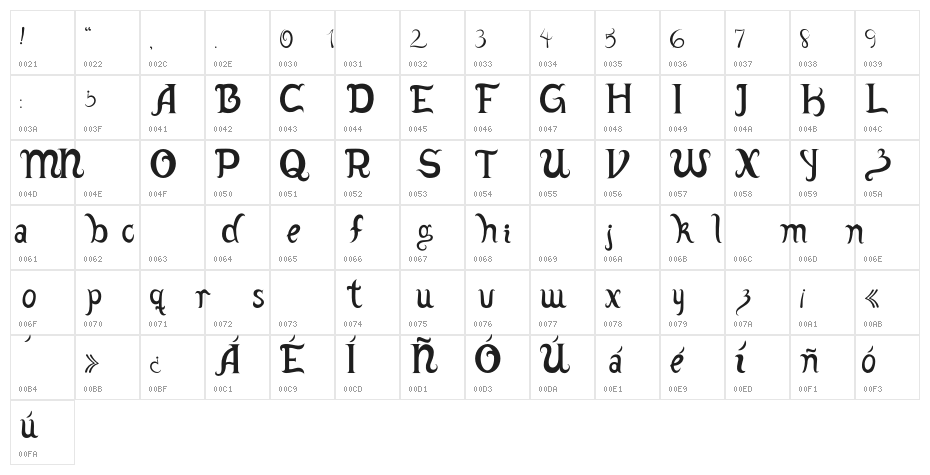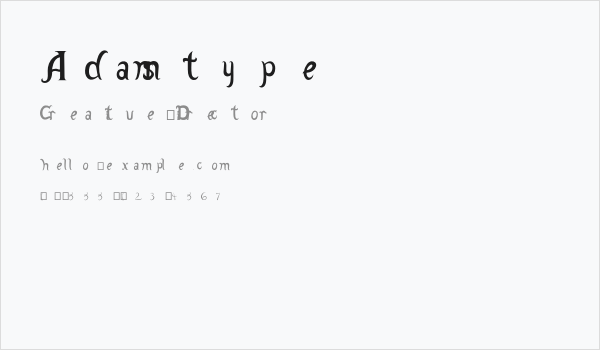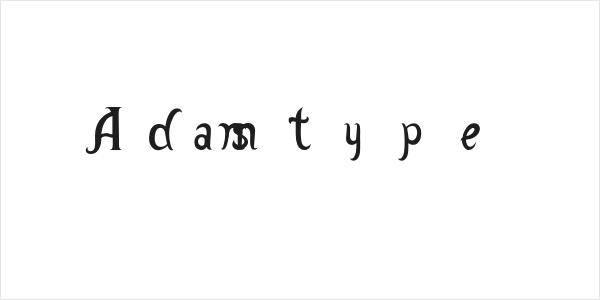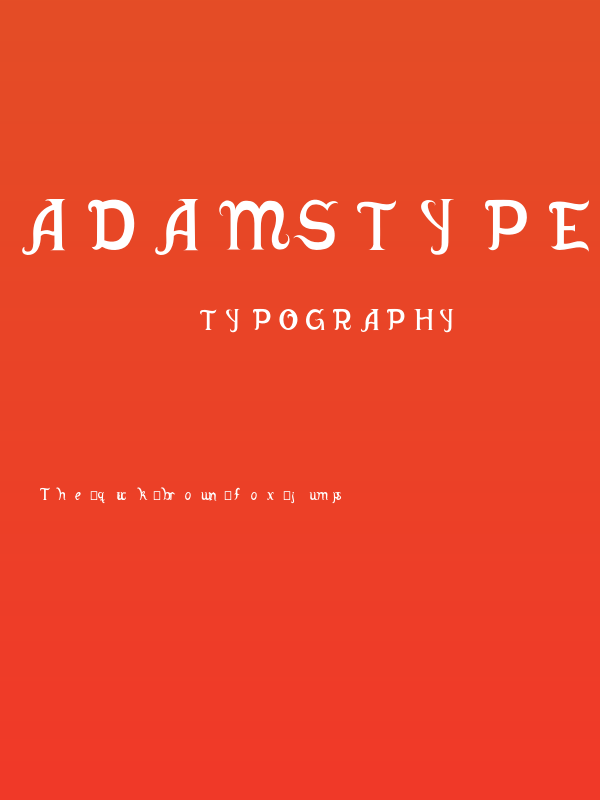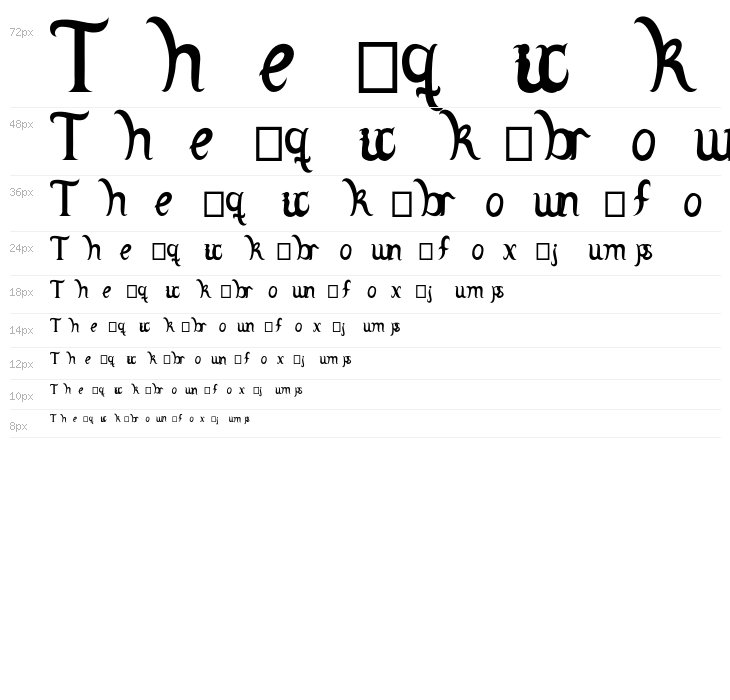
Adamstype Font
| Caso d'uso | Logos, Invitations, Posters |
| Progetti proposti | Ideal for projects that require a touch of elegance and artistry, such as wedding invitations, luxury branding, or decorative posters. |